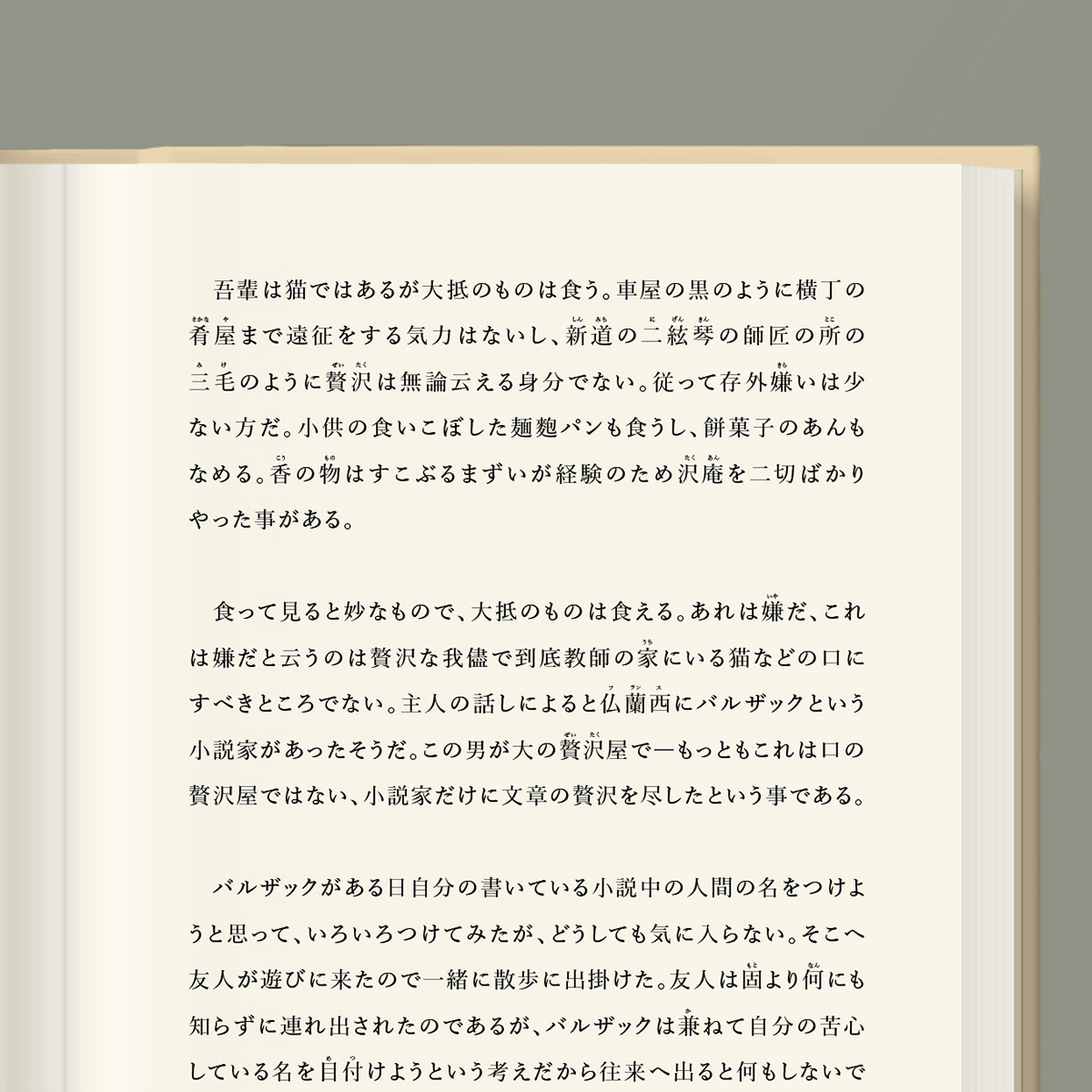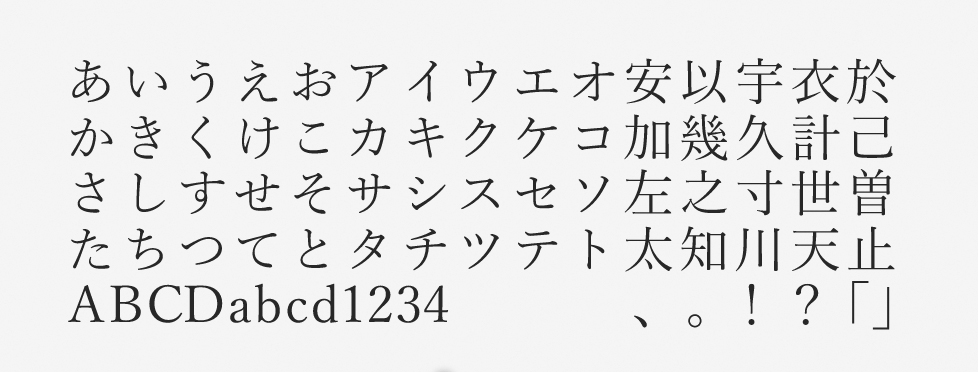
「游明朝体」について
游明朝体は、字游工房による初の独自書体として登場しました。「時代小説が組めるような明朝体」をキーワードとして開発が進められ、字游工房での販売が開始されたのは2002年です。モリサワで提供されている游明朝体は6つのウエイトで展開されており、書籍のデザインなどでは1冊を通して統一感のある見映えを実現できます。
「游明朝体」の特徴
時代小説を念頭に置いて開発された游明朝体は、クラシカルな印象を与えます。穏やかで柔らかな雰囲気の落ち着いたフォントです。文字の空間が均一に見えるように設計されており、丸みのあるウロコや柔らかな曲線の効果で上品な印象も与えます。
書籍の本文に最適な書体ですが、ウエイトのバリエーションを活用して見出しなどでも有効です。見出しに特化したウエイトはBとE。これらの骨格はほかのウエイトとはやや異なり、ふところが狭くて引き締まっています。
游明朝体は、本文対応の明朝体としての代表格です。開発のコンセプト通り、まさに「時代小説が組めるような明朝体」で、印刷媒体には必須と言えるでしょう。今回の作例では本文を横組みにしていますが、縦でも横でもまったくストレスなくスラスラと読めるフォントではないかと思います。
「游明朝体」の書体情報